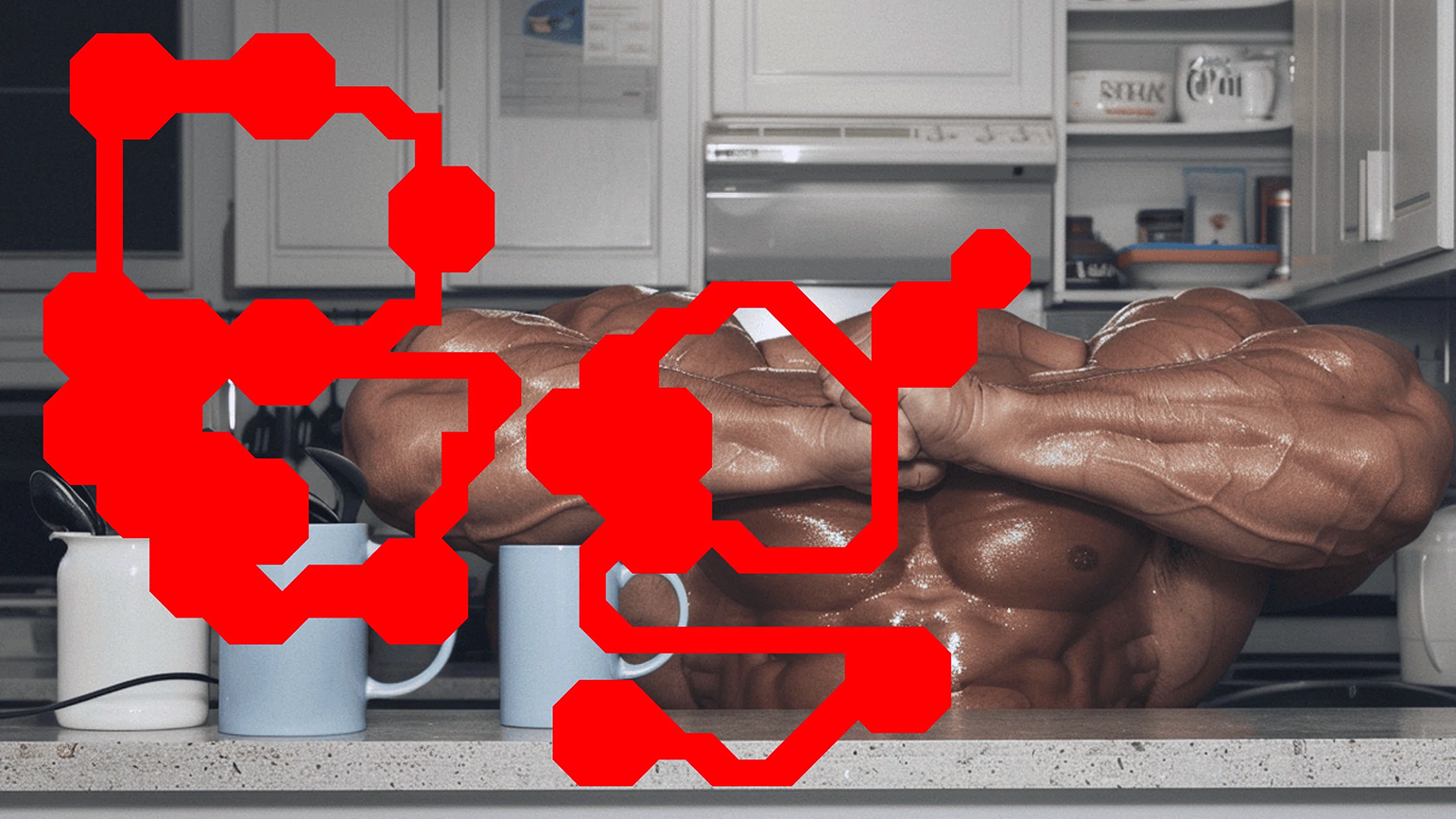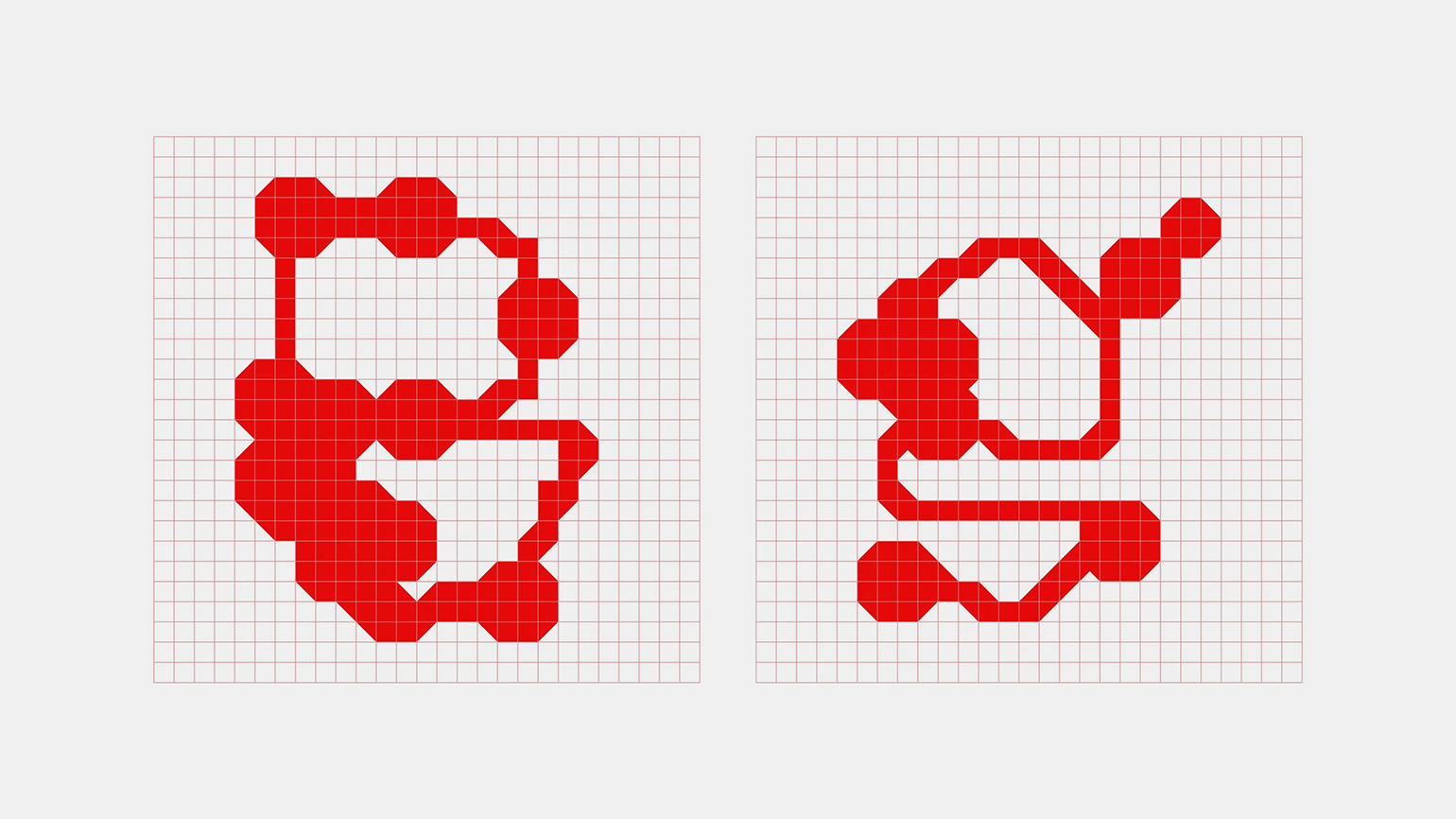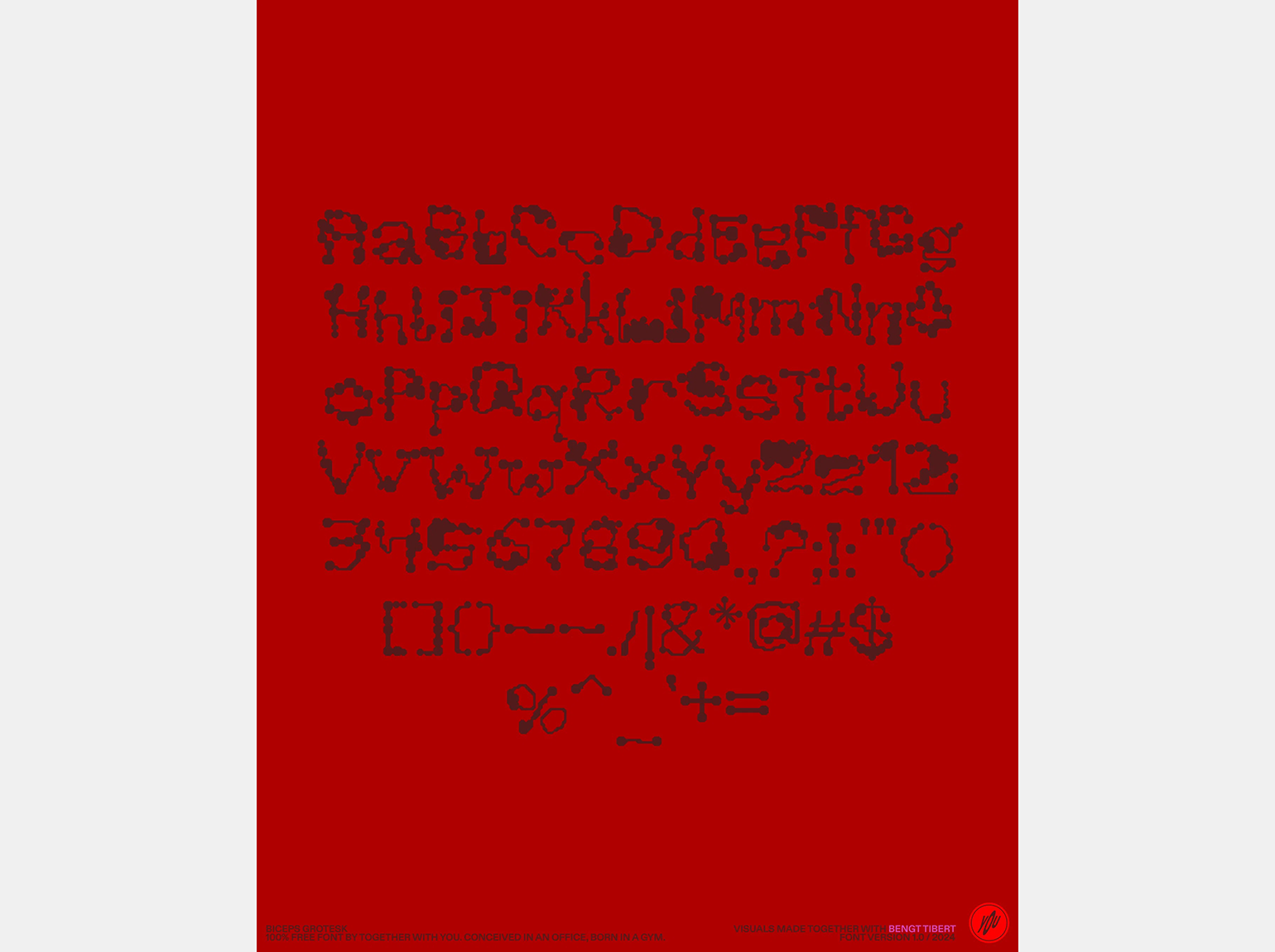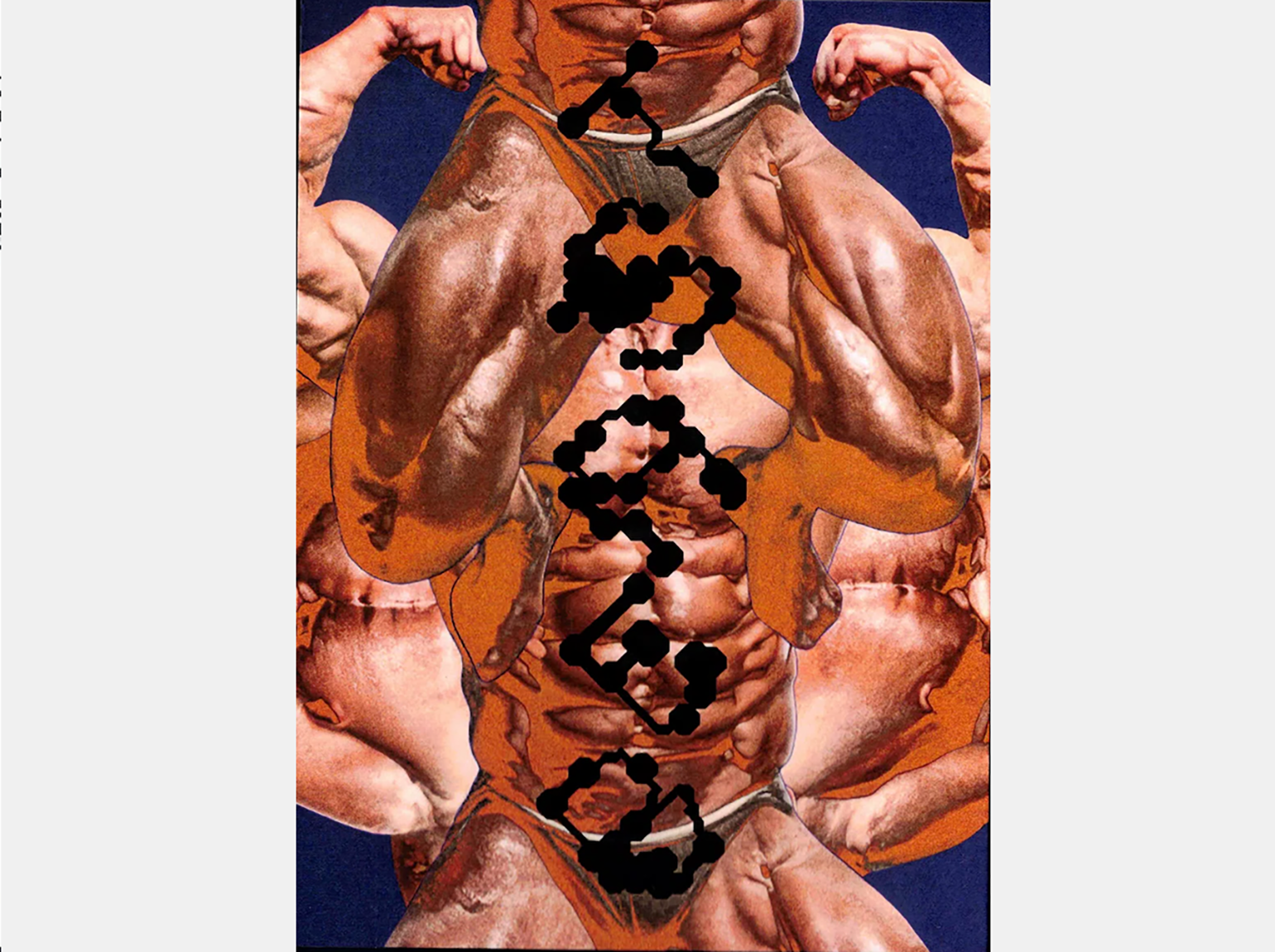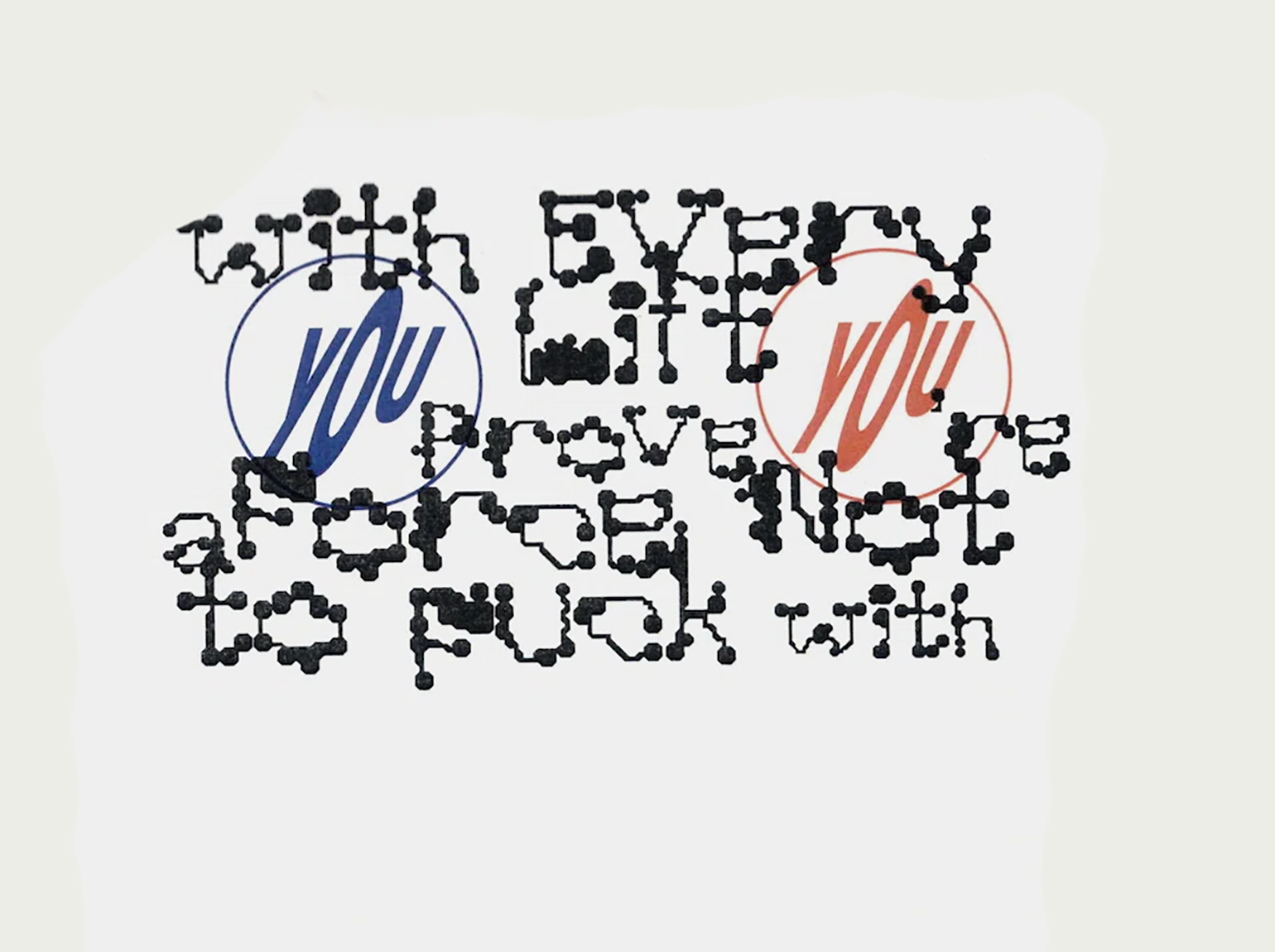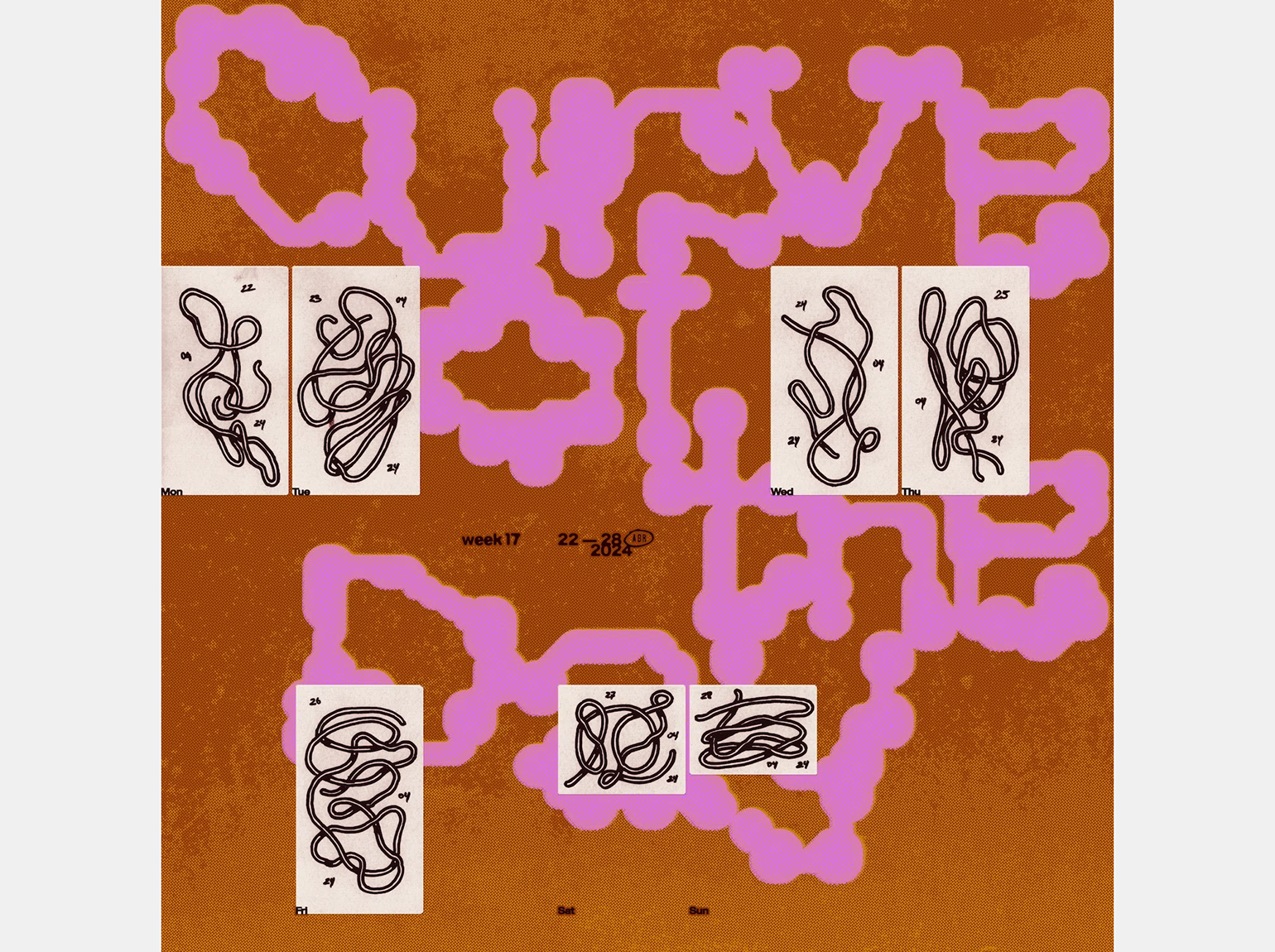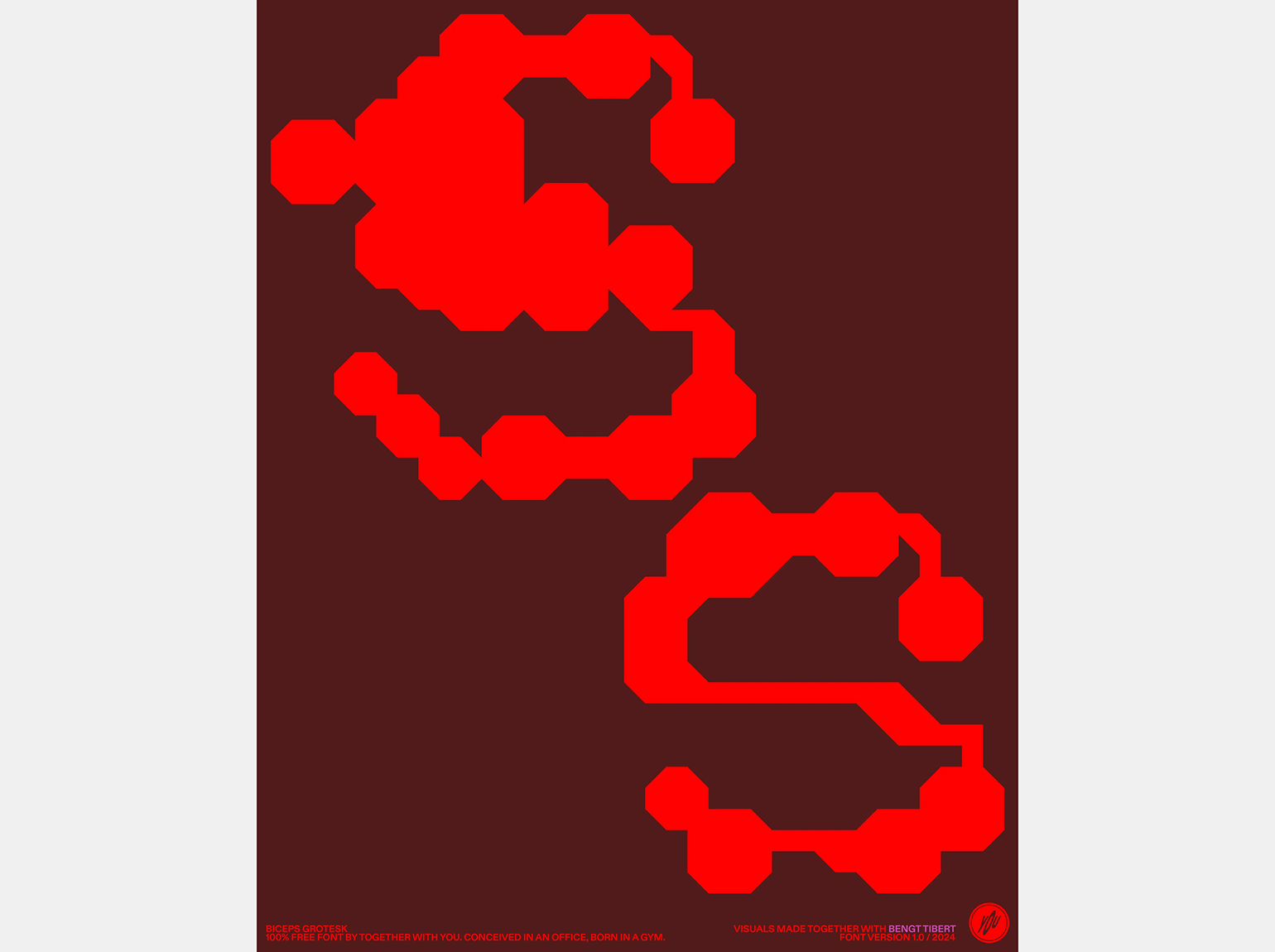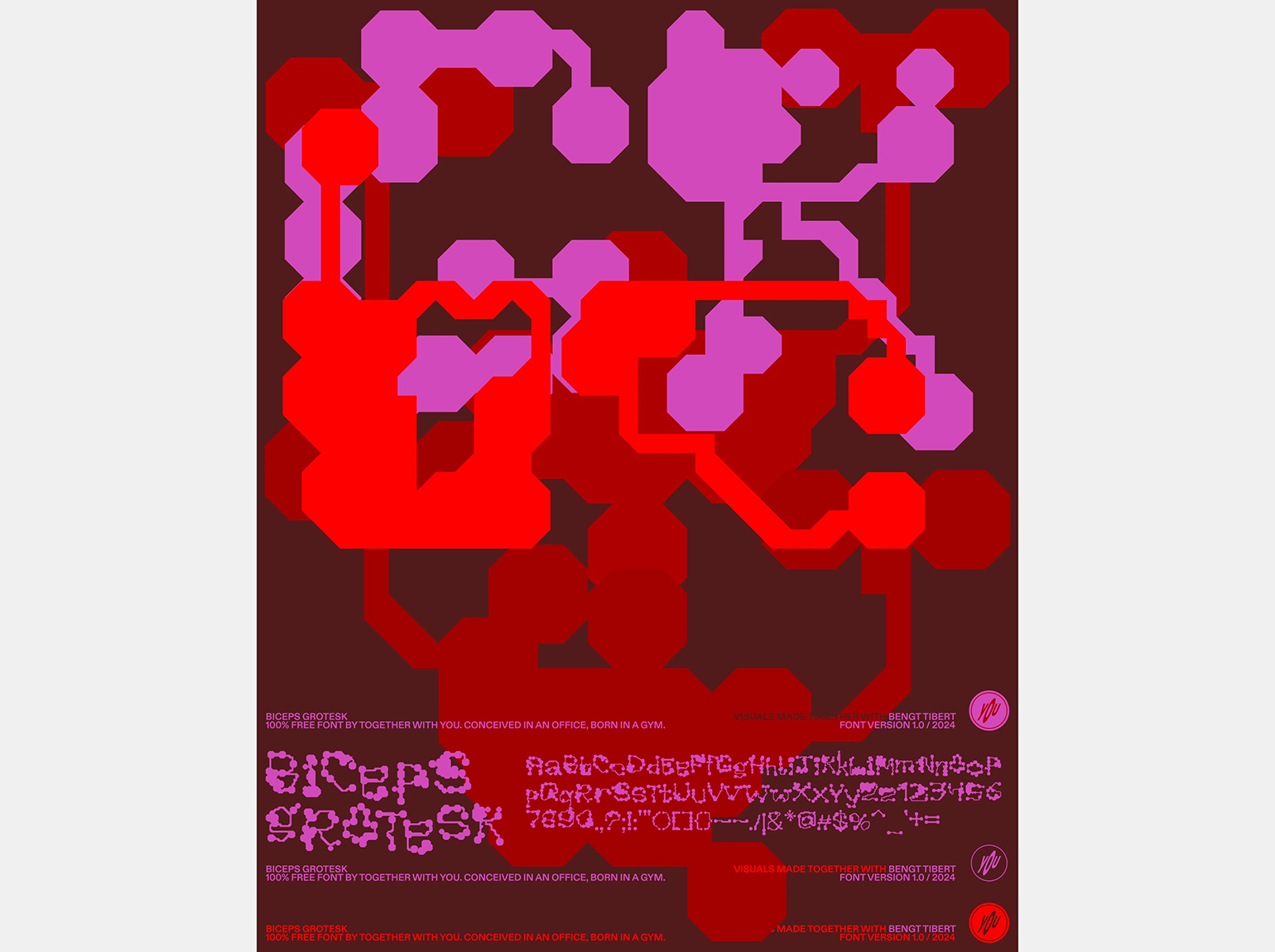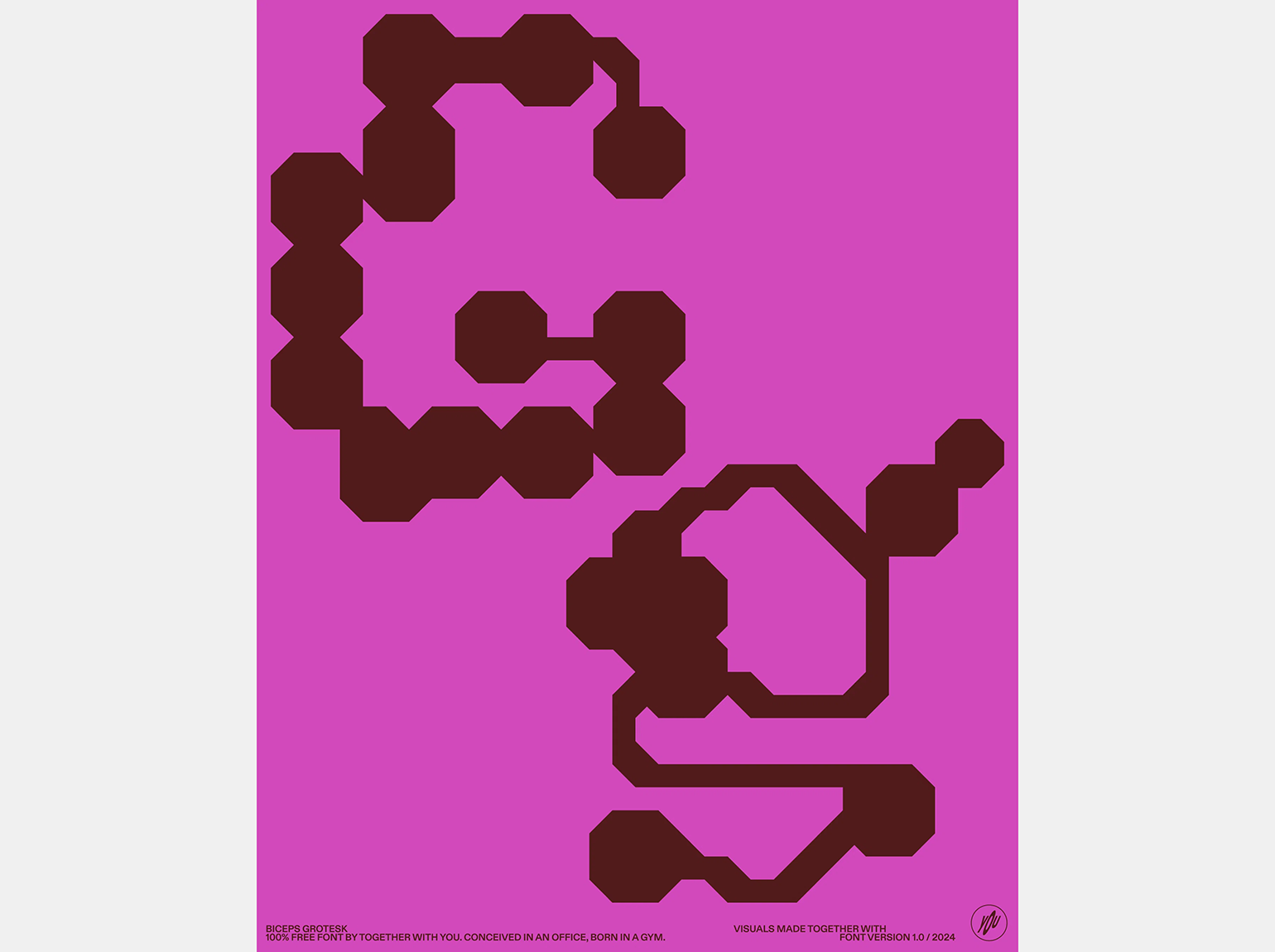
Biceps Grotesk: шрифт с «модульными мышцами»
Его выпустила студия Together With You.
Про новый бесплатный шрифт рассказали в видеоролике, который создал художник Бенгт Тиберт. Он похож на ролик, сгенерированный искусственным интеллектом: в начале изображён офис, в котором группа мужчин демонстрирует неестественно большие мускулы, а потом показана каждая буква шрифта Biceps Grotesk.
Соавтором шрифта стал Артём Тарасов, который рассказал изданию It’s Nice That, что идея шрифта возникла случайно во время работы над коммерческим проектом по созданию айдентики:
«Мы наткнулись на форму гантели, составленную из квадратных и треугольных модулей, и подумали, что это круто, просто потому что странно. Сначала мы добавили руки, чтобы держать гантели, а потом мем вышел из-под контроля».
По его словам, рисовать глифы таким образом было очень весело. Вскоре буквы стали превращаться в абстрактные органические формы. Biceps Grotesk вписывается в строгие модульные сетки, но нарушает другие типографские правила. Его формы абстрактны, но при этом он достаточно читаемый. Шрифт можно скачать бесплатно, он подходит для создания типографики или абстрактных векторных иллюстраций.